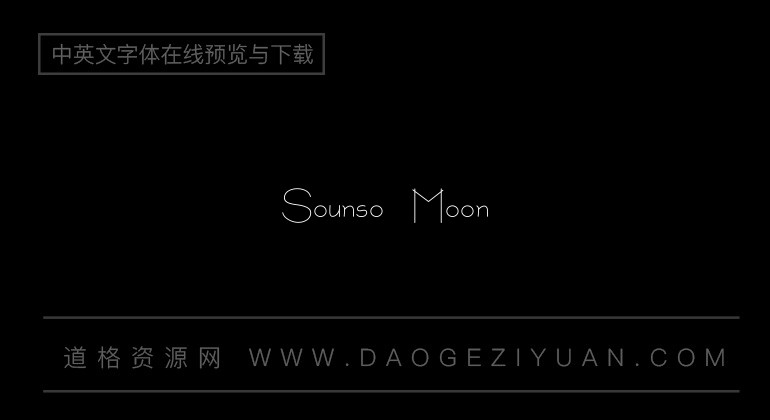
Sounso Moon
Sounso Moon字体是一种优美而独特的字体,源自日本。它的设计灵感来自于日本传统艺术和文化,以及现代设计的元素,创造出一种深受人们喜爱的字体。 Sounso Moon字体的外观非常简洁,线条流畅。它的特点在于字母的笔画运用了圆润的曲线,使字母具有艺术美感。整个字体看起来很流畅、柔和,让人感觉舒适、自然。 Sounso Moon字体适用于各种文本,特别是设计和创意领域。它可以为文字添加一份优雅和个性,让设计作品更加出色。无论是在印刷品、海报、标志、宣传册等各种设计项目中,Sounso Moon字体都可以起到很好的装饰作用。
Sounso Moon是一款非常不错的手写艺术字体,具有很好的视觉感,适合于文化类的宣传设计、商业类品牌的广告和产品包装设计以及个性化文字排版等较多场景。